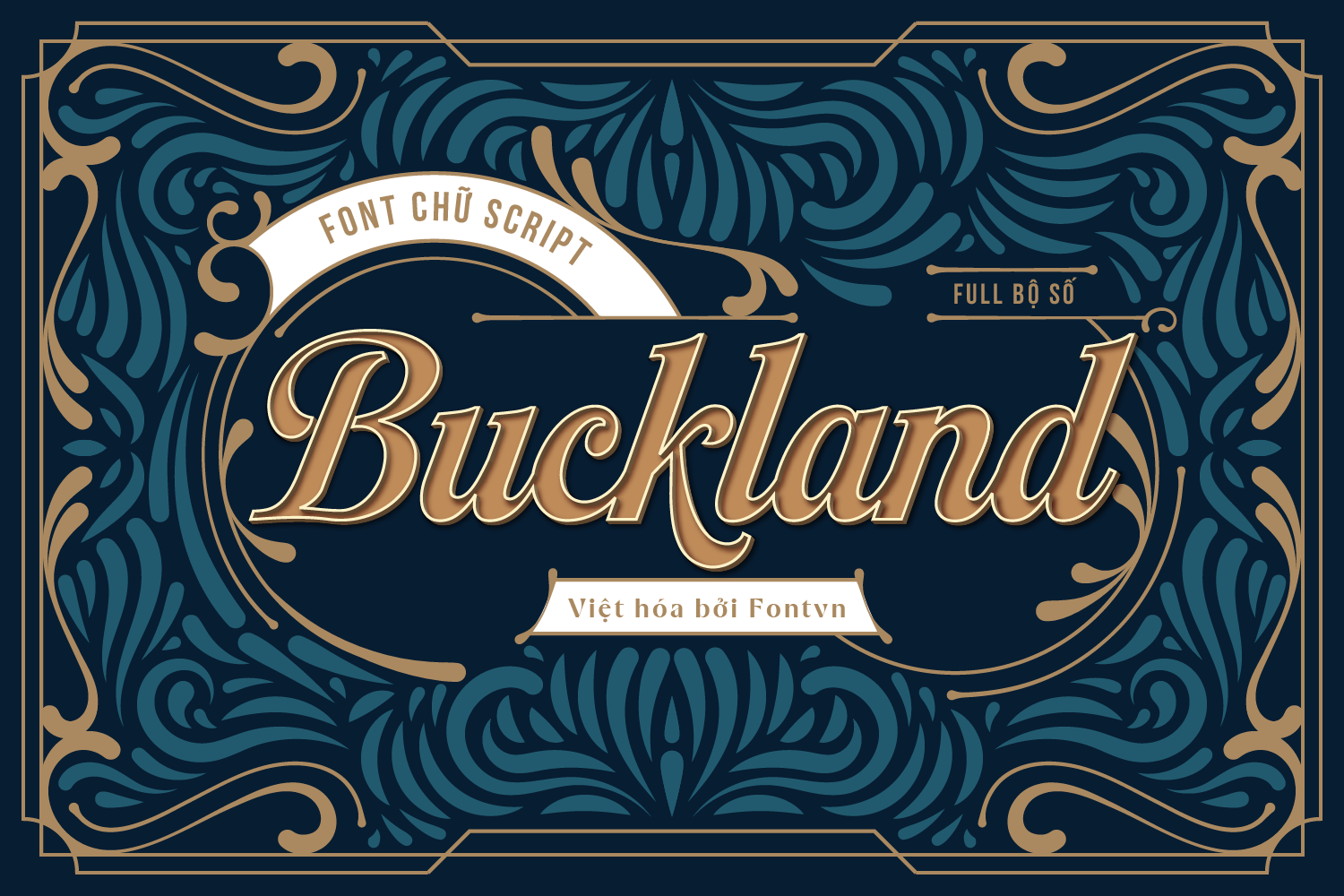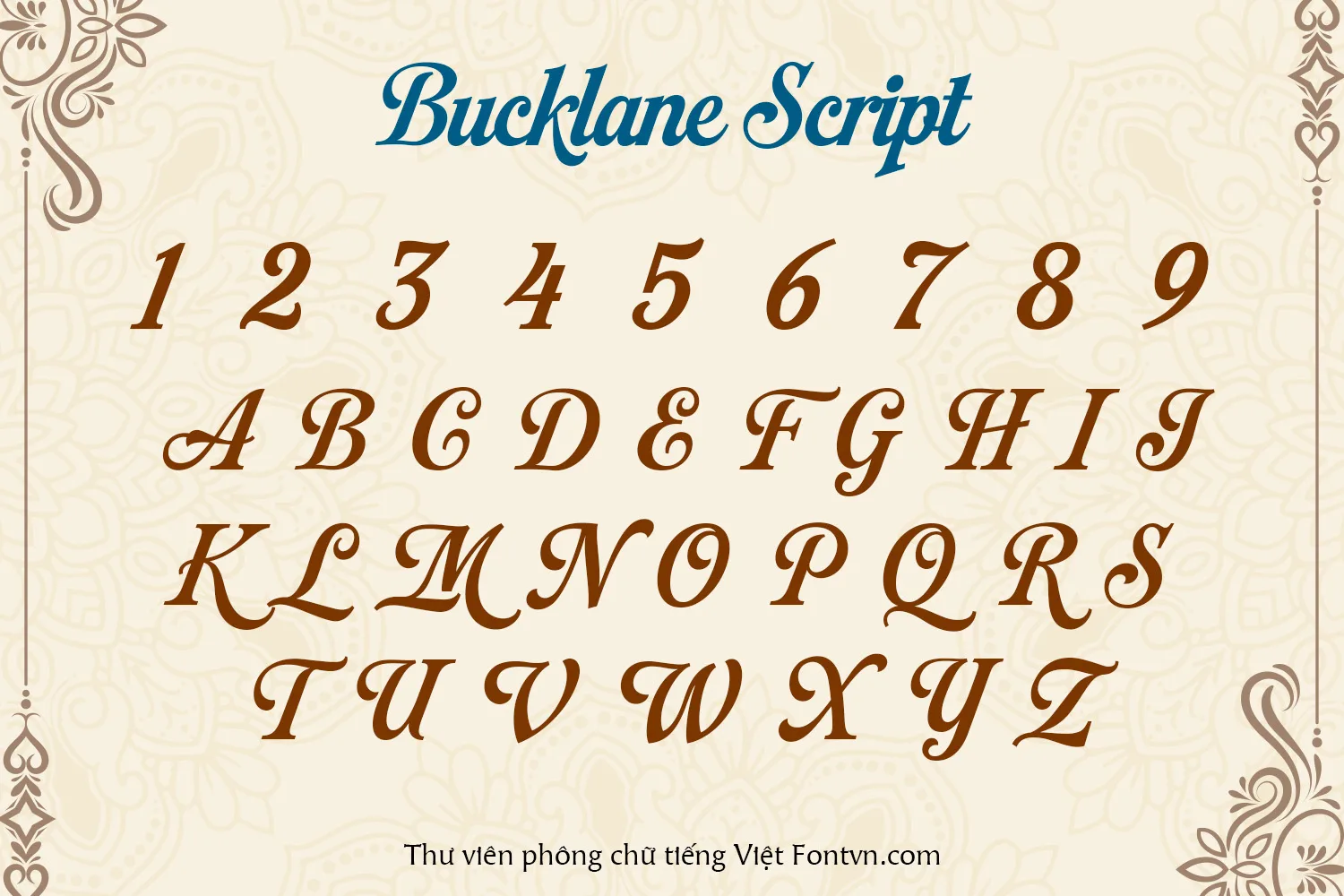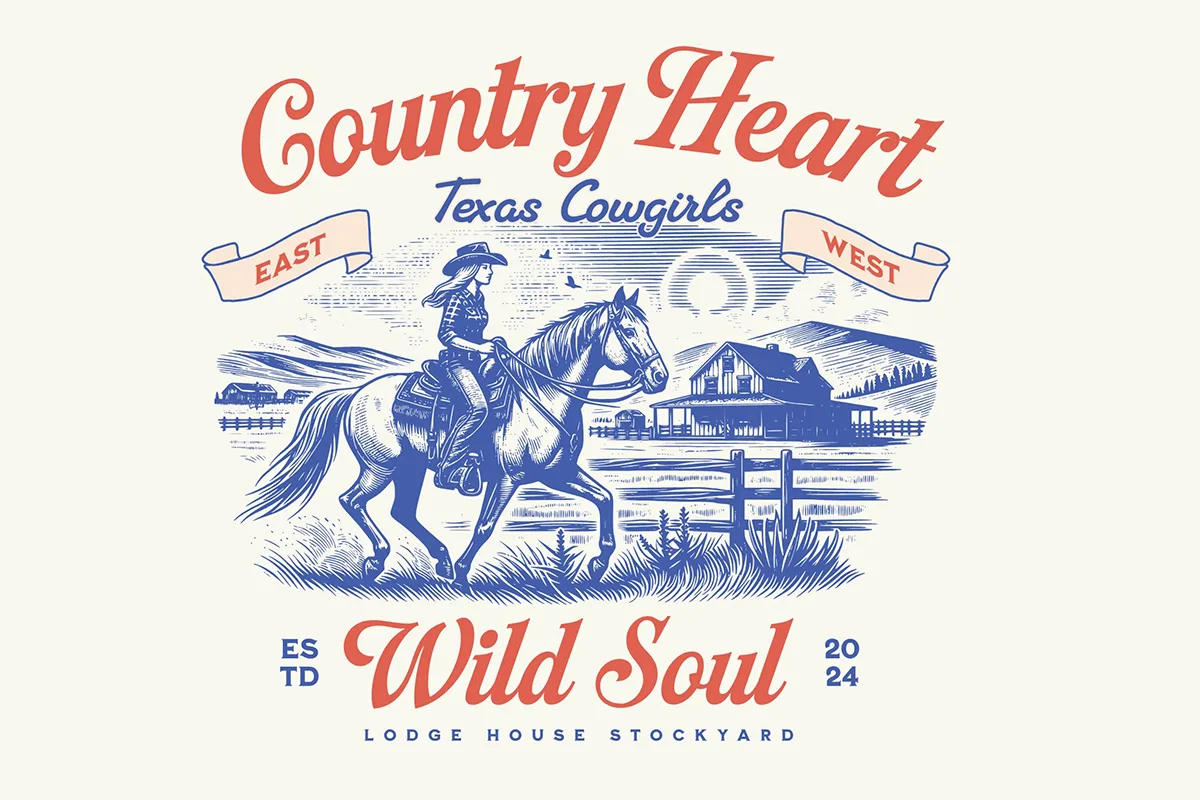
DVN Bucklane Script Việt hóa – Phiên bản làm lại dấu và đủ bộ số
DVN Bucklane Script Việt hóa là kiểu chữ mang phong cách thư pháp cổ điển, sang trọng và bay bướm, rất lý tưởng cho các thiết kế đề cao tính thẩm mỹ và cảm xúc. Với những nét chữ uốn lượn mềm mại, font này thường được sử dụng trong các ấn phẩm mang tính cá nhân hoặc cao cấp như thiệp cưới, thiệp mời, tiêu đề sản phẩm thủ công, bao bì mỹ phẩm, poster thời trang hoặc logo thương hiệu mang phong cách thanh lịch.
Phiên bản Việt hóa lần này không chỉ bổ sung đầy đủ dấu tiếng Việt với cách đặt dấu mượt mà, hợp lý, mà còn hoàn thiện thêm bộ số và ký tự cơ bản, giúp font dễ dàng ứng dụng trong cả các thiết kế hiện đại và in ấn thương mại. Dù dùng để tạo điểm nhấn nổi bật trong một dòng chữ hay dùng nguyên một đoạn tiêu đề, DVN Bucklane Script luôn giữ được sự duyên dáng và chuyên nghiệp trong từng chi tiết.